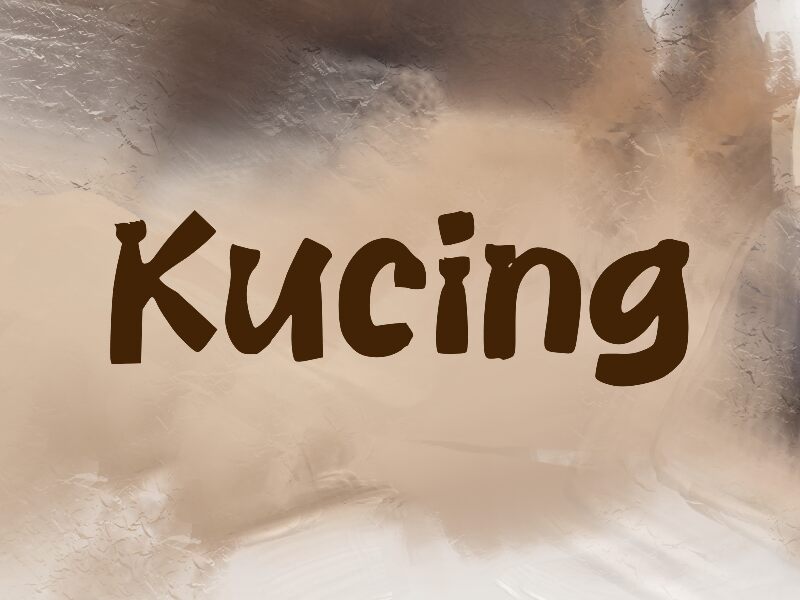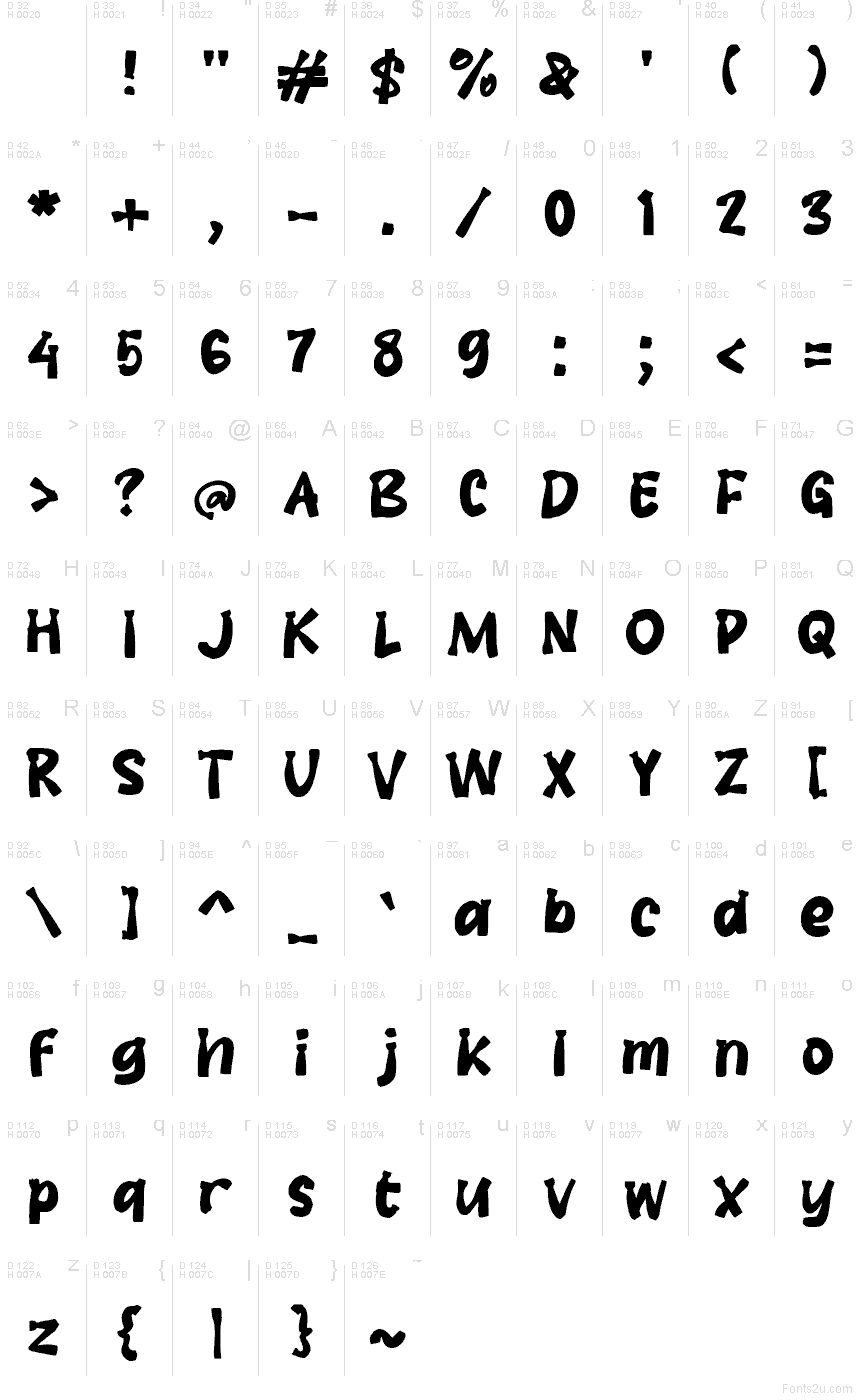
Kucing
Kucing от Wep — это бесплатный мультяшный дисплейный шрифт с «лохматым», рукописным характером и легкой кошачьей ухмылкой. Буквы выглядят плотными, мягкими и нарочито неровными, с округлыми изгибами, узкими соединениями и острыми штрихами, которые напоминают когти или кошачьи ушки, не превращая шрифт в нечто нелепое.
Он отлично подходит для обложек детских книг, упаковки снеков, игривых заголовков на постерах, стикеров и оформления соцсетей, где нужно что-то дерзкое, а не аккуратное. Kucing — это бесплатный шрифт, который также хорош для коротких логотипов, графики для стримеров и акцентных слов, ведь благодаря своему неровному ритму он оживляет даже самые короткие надписи.